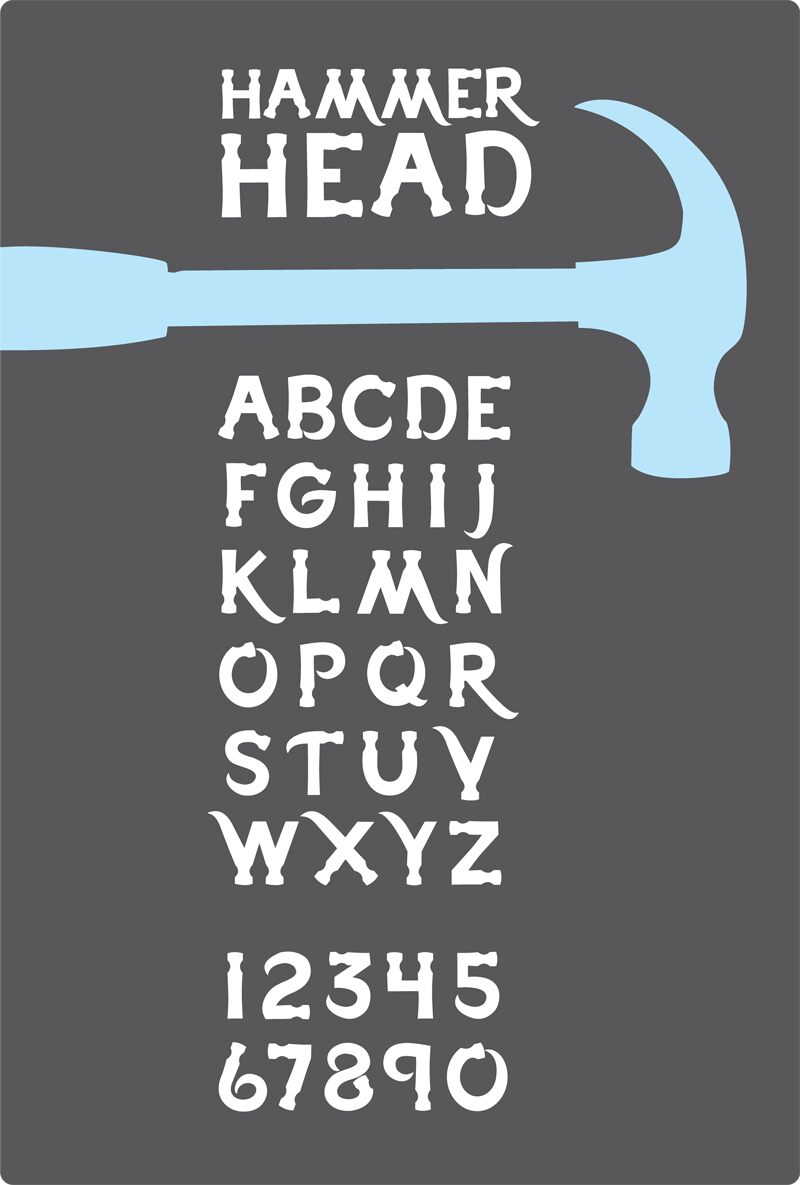
Hammerhead Italic von Kimmy Kirkwood ist eine dekorative Display-Schrift mit einer markanten, geneigten Haltung, die wirkt, als wäre sie aus schwerem Stahl geschmiedet. Kräftige Striche, kantige Schultern und die charakteristischen „Hammerhead“-Schnitte an den Verbindungsstellen verleihen jedem Wort einen rauen, industriellen Swagger, während der Vorwärtsdrang für Schnelligkeit und Wirkung sorgt. Sie wirkt laut und präsent, noch bevor Sie eine Farbe hinzufügen.
Mit Hammerhead Italic knallen Ihre Überschriften nur so auf die Seite. Damit ist diese kostenlose Schrift die perfekte Wahl für Poster von Rock- oder Metal-Konzerten, Cover von Action-Spielen, Branding im Extremsport-Bereich, Logos für Werkzeuge oder Hardware sowie Filmtitel. Der straffe Rhythmus der Buchstaben funktioniert auch bei großen Größen hervorragend, wo die gemeißelten Kanten erst richtig zur Geltung kommen. Kombinieren Sie sie für Fließtext mit einer einfachen geometrischen Sans-Serif in einem leichteren Schnitt, damit der Fokus auf den wuchtigen, skulpturalen Formen von Hammerhead bleibt.